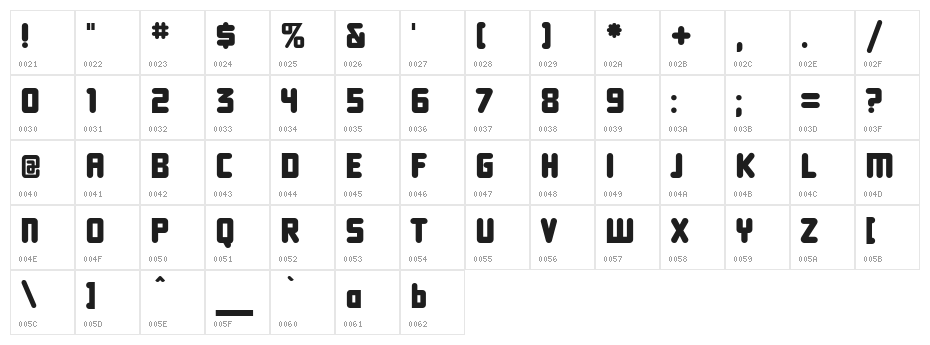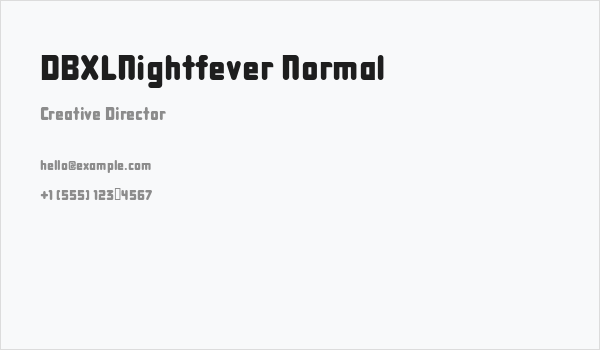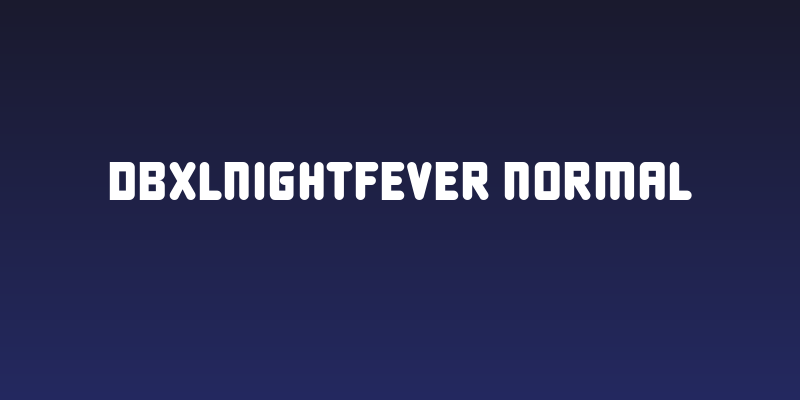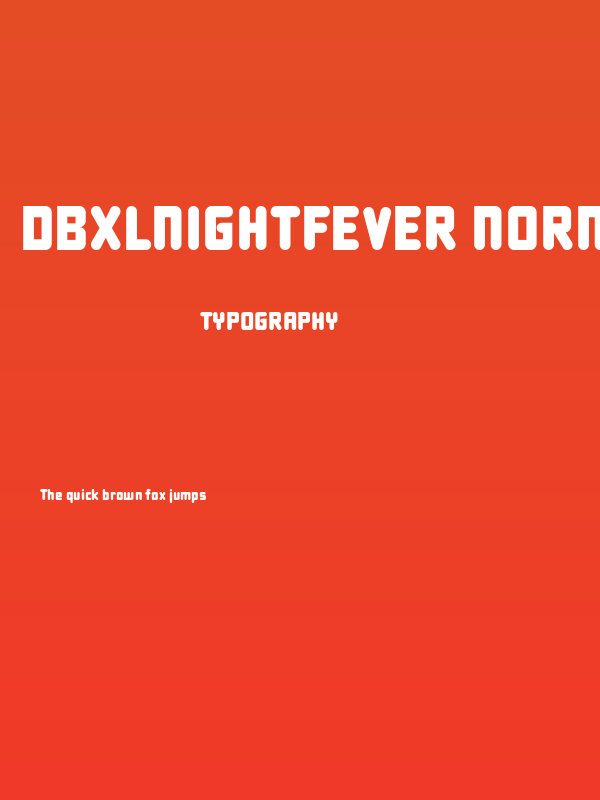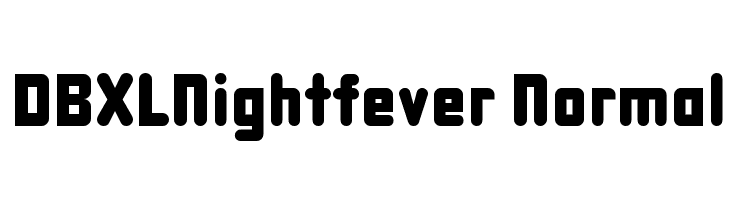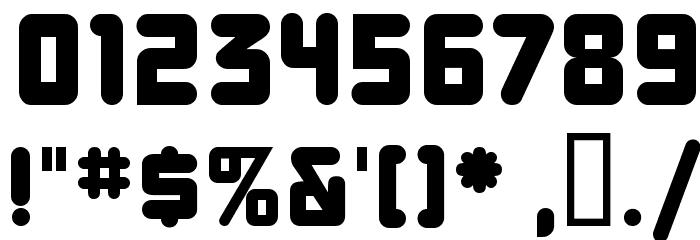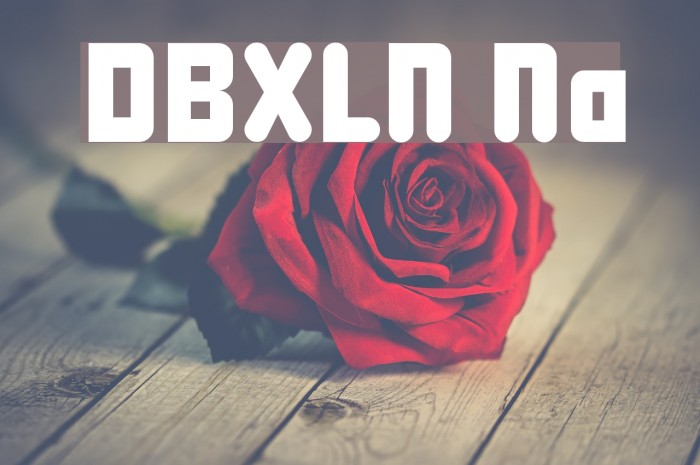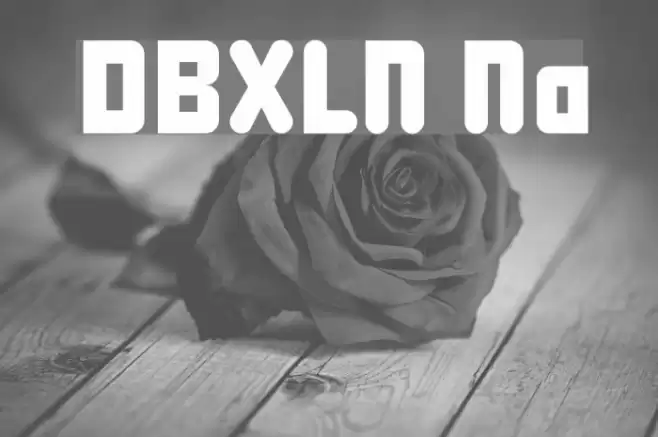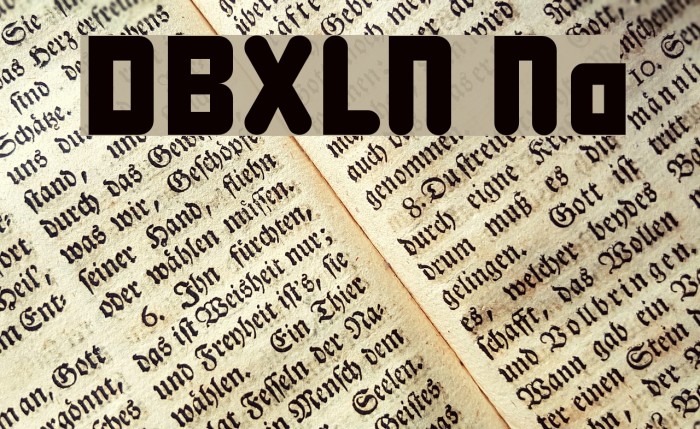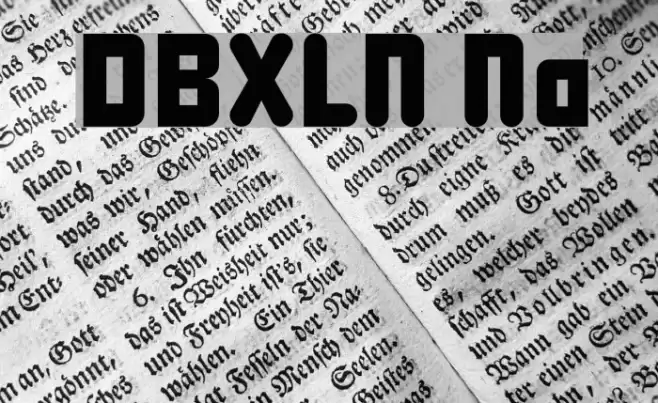
DBXLNightfever Normal Font
| Proiecte propuse | Ideal for branding projects, posters, and headlines where a modern and approachable look is desired. |